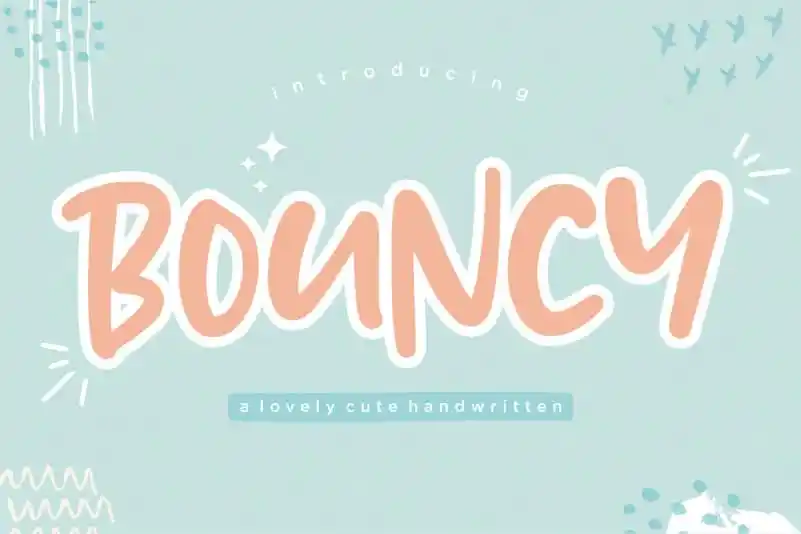
Bouncy Lovely Handwritten Font – Fonte Grátis
Bouncy Lovely Handwritten Font
A ‘Bouncy Lovely Handwritten Font’ é uma criação artística para quem aprecia a arte do escrita à mão com um toque especial. Essa fonte retrata perfeitamente a essência do estilo handwritten, combinando movimentos fluidos e cores suaves em cada letra. Perfeita para aplicar em projetos de embalagens de produto, criação de marca, revistas, redes sociais, festas de casamento ou qualquer projeto que deseje expressar de uma maneira mais pessoal e emotiva. Com suas linhas levemente onduladas e seus traços delicados, a Bouncy Lovely Handwritten Font oferece um tom suave e descontraído que se adequa perfeitamente para criar um impacto visual único em qualquer projeto. Este é um recurso ideal tanto para profissionais de design gráfico quanto para artistas criativos que buscam dar ao seu trabalho aquele toque especial. Seja este o próximo passo para personalizar sua marca, expressar uma mensagem específica ou decorar a superfície de seus projetos com um charme único e sofisticado, certamente a Bouncy Lovely Handwritten Font será uma escolha ideal.